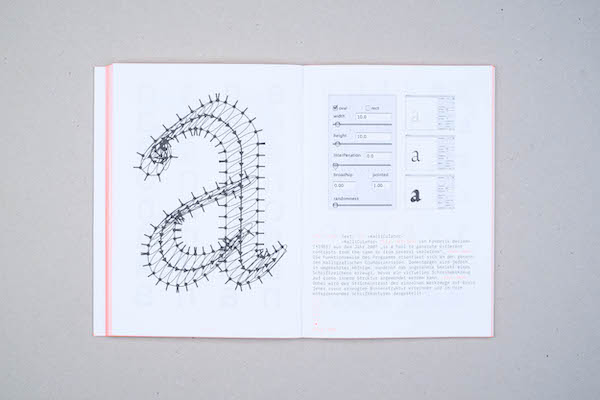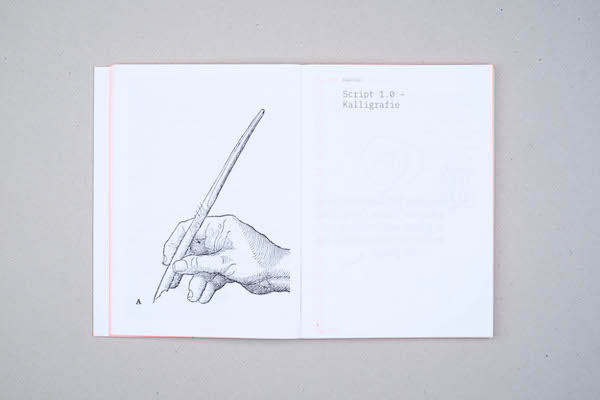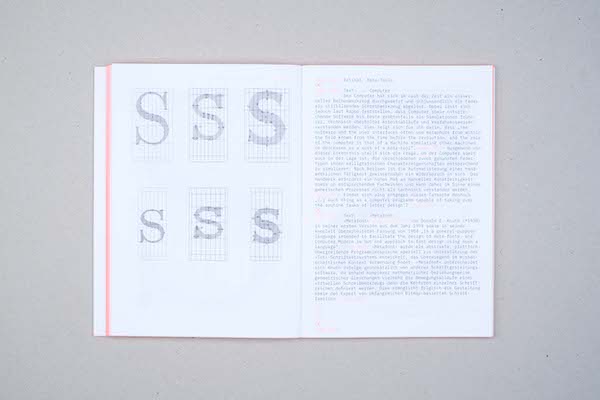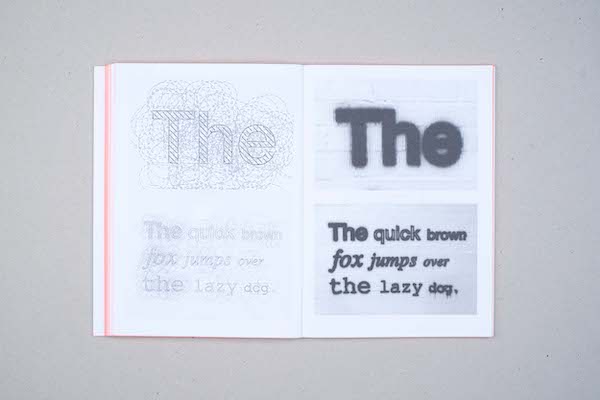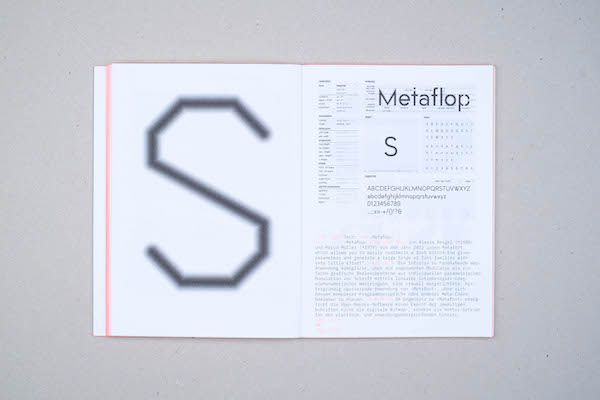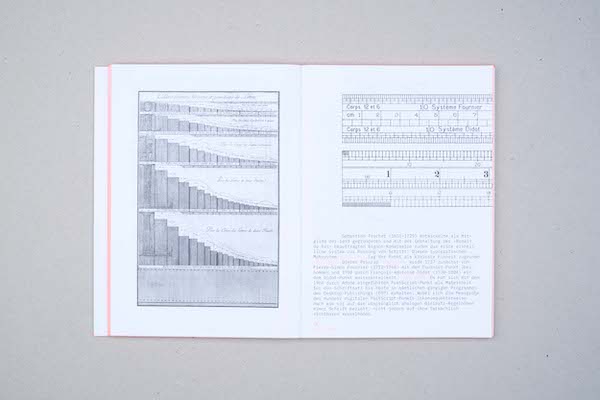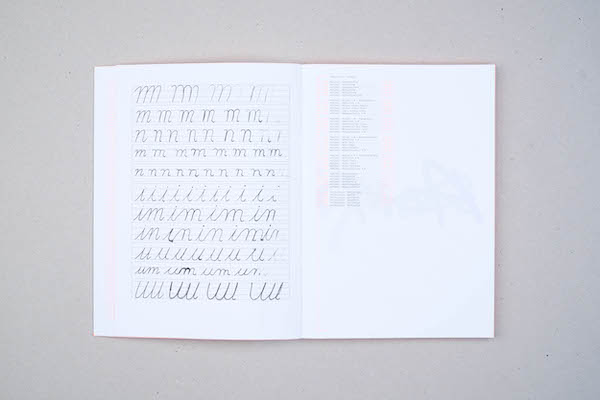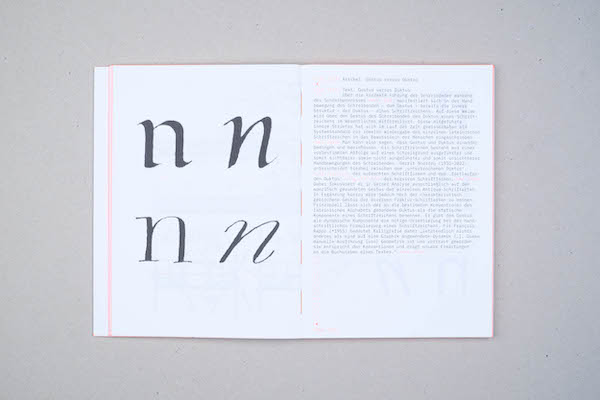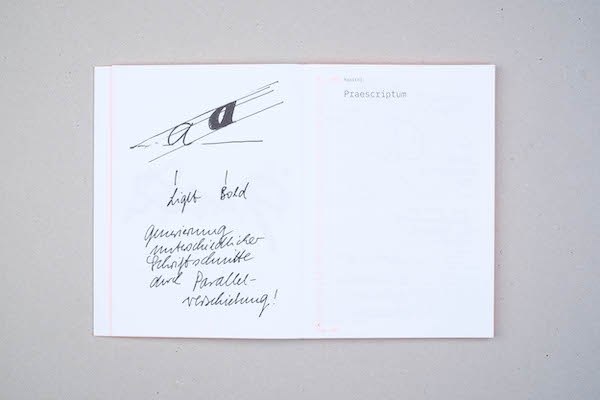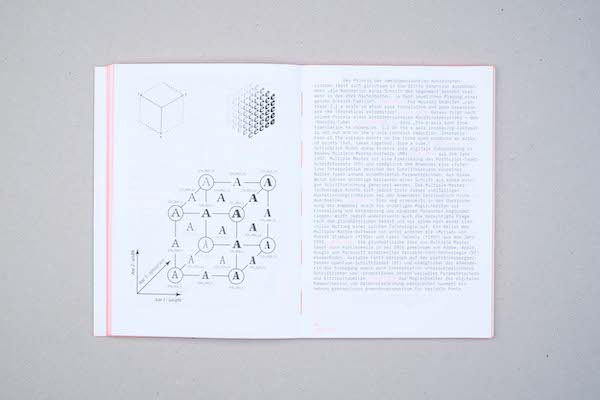
Christian Stindl
Script – Über das Wesen der Schrift
→ Genügen die bestehenden Schriftsysteme noch, um in Zukunft – auch mit Maschinen – zu kommunizieren?
→ Eine grundlegende Reflexion zum Status quo unserer Schrift und welche Entwicklung sie in Zukunft nehmen wird
Unsere bestehenden Schriftsysteme gehören zu den bedeutendsten soziokulturellen Errungenschaften – die Schrift beeinflusste sowohl unser Denken als
auch Handeln massgeblich, kein technischer Fortschritt wäre möglich gewesen.
Die aktuellen technologischen Veränderungen – Internet der Dinge, Industrie 4.0, KI – erfordern aber einen strukturellen Wandel, der sich in der Art und Weise, wie wir denken, kommunizieren und produzieren, niederschlagen wird.
Mit diesem Positionspapier eröffnet der Autor den
längst überfälligen Diskurs hinsichtlich der aktuell gängigen Praxis im Bereich der Gestaltung von Schrift. Er kritisiert dabei die offenkundige Diskrepanz zwischen der stetig zunehmenden Anzahl an formellen Neuinterpretationen von Schriftzeichen einerseits sowie der mangelnden strukturellen Reflexion des lateinischen Zeichensystems.
Christian Stindl begibt sich auf die Suche nach dem Wesen der Schrift der Zukunft. Er hinterfragt ihre heutige Relevanz und prognostiziert gleichsam
den Untergang des lateinischen Zeichensystems. Ein grundsätzliches Umdenken seitens der Schrift-gestalter sowie eine notwendige Neuausrichtung dieser Disziplin sind daher seiner Ansicht nach unbedingt erforderlich.
Das Kapitel «Script 1.0 – Kalligrafie» beschäftigt sich mit dem Prozess des Schreibens und erläutert das Verhältnis von Schreibbewegung und -werkzeug. «Script 2.0 – Typografie» erörtert die verschiedenen Arten des Beschreibens von Schriftkonturen sowie ihr
jeweiliger Einfluss auf die entsprechende Schriftform eingehend. «Script 3.0 – Metatypografie» zeigt innovative digitale Werkzeuge zur Erzeugung von Schrift und ihre Herausforderungen für Schriftgestalter. «Script 4.0 – Hypertypografie» bietet schliesslich einen Ausblick auf die zu erwartenden Auswirkungen auf das bestehende Schriftsystem einerseits sowie auf die zukünftige Tätigkeit des Schriftgestalters andererseits.